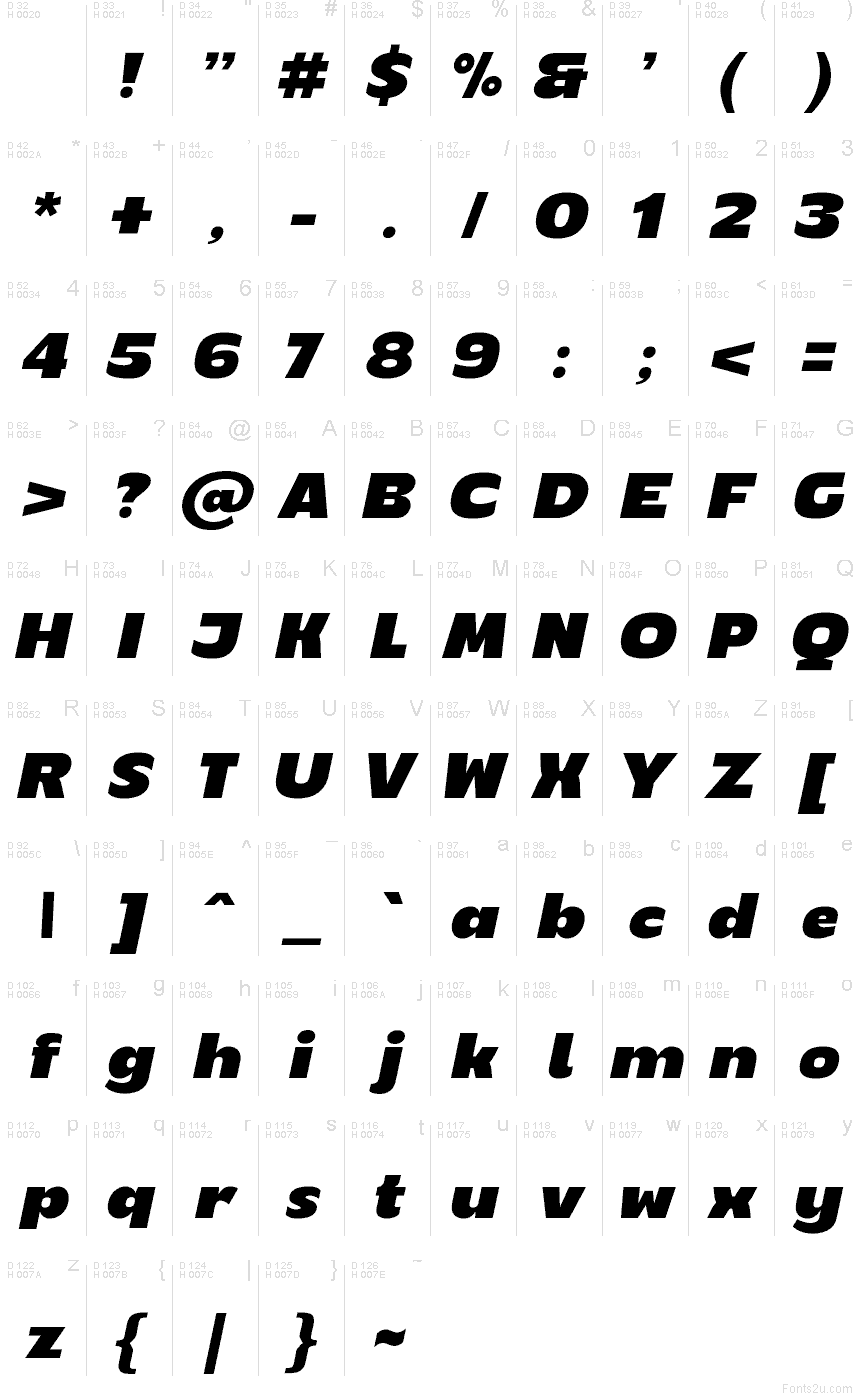
Písmo Mertune Italic od Muhamada Fikryho Nuralifa z Fikryal Studio je tučné kurzívní bezpatkové písmo s výrazným směřováním vpřed. Jeho silné, šikmé tahy působí, jako by byly vyříznuté z vinylu – jsou úderné, razantní a trochu agresivní, takže nadpisy vypadají svižně, i když je sdělení jednoduché. Kompaktní rozestupy udržují text vizuálně celistvý a čitelný.
Mertune Italic využijete při sportovním brandingu, značení streetwearu, obalech energetických nápojů, herních promo akcích, plakátech technologických akcí, úderných miniaturách na YouTube a odvážných reklamách na sociálních sítích. Vyzkoušejte ho ve velkém měřítku s dostatkem prostoru a doplňte ho klidným geometrickým bezpatkovým písmem v běžné tloušťce, aby toto bezplatné písmo skutečně vyniklo.